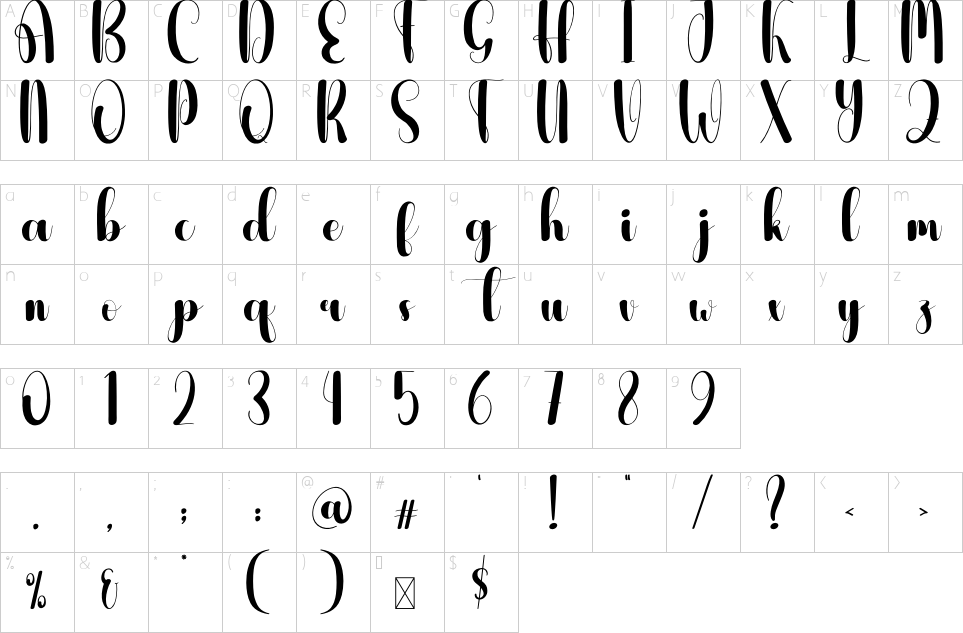
A fonte Azalea é uma escolha natural e envolvente para qualquer projeto gráfico, especialmente em ambientes visuais naturais e amigáveis. Desenvolvida por William Jhordy, a Azalea traz um ar fresco e autêntico ao seu projeto. Seu design é suave e minimalista, adequado para uso em nomes de produto, logotipos e materiais de marketing. Com uma paleta de cores suaves e uma tipografia agradável aos olhos, a Azalea é uma opção ideal para qualquer projeto que busque uma solução elegante e de fácil leitura. É perfeita para aqueles que valorizam um estilo natural e de fácil combinação, sem esquecer de oferecer uma identidade visual única. Com um download de mais de 600 vezes, é evidente que a comunidade de designers gosta muito do seu desempenho e facilidade de uso.